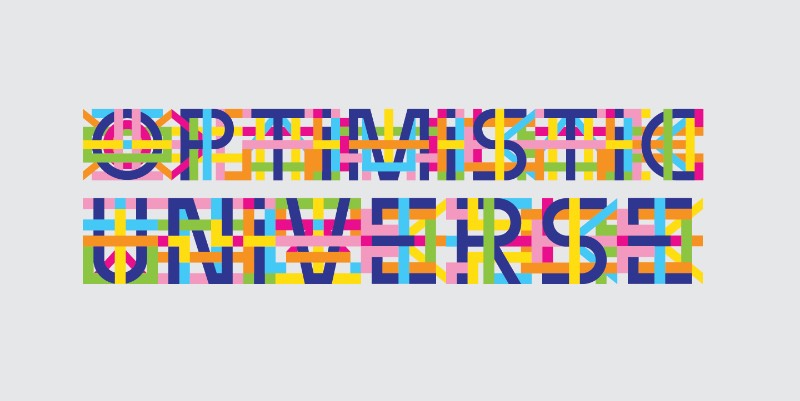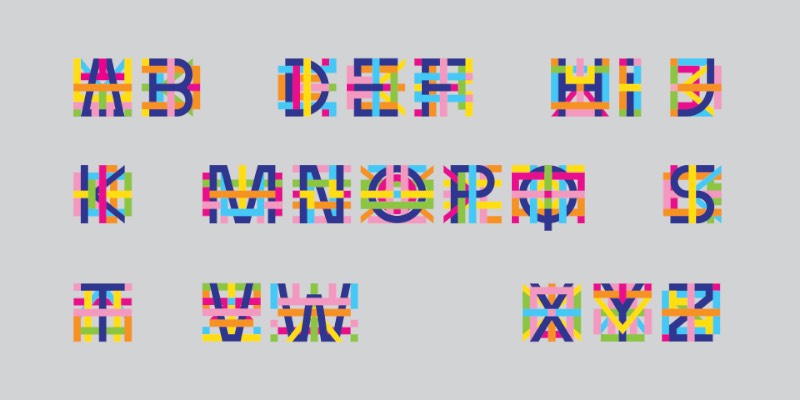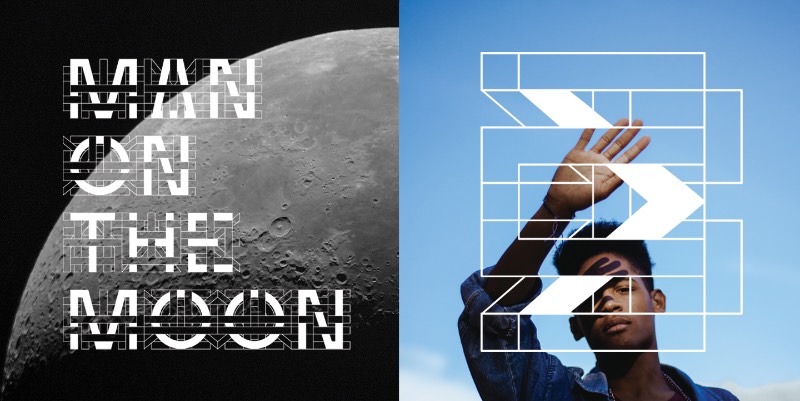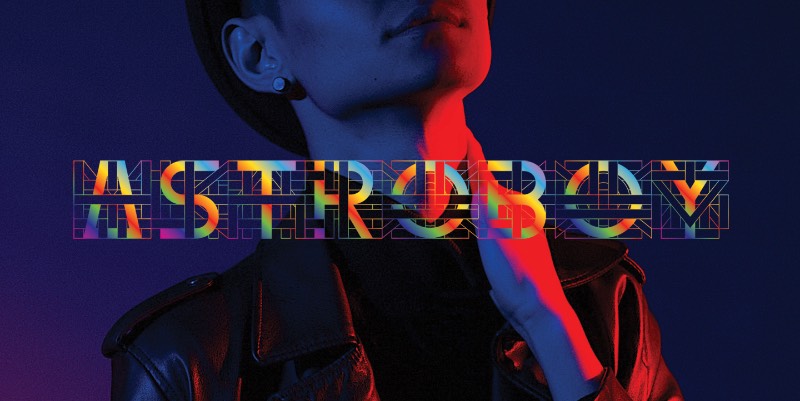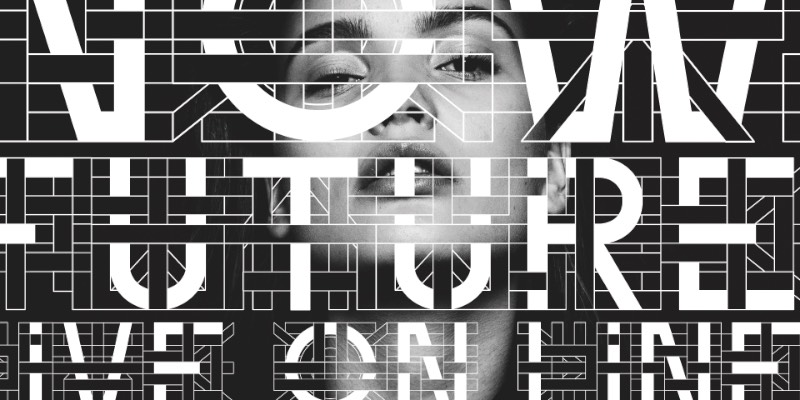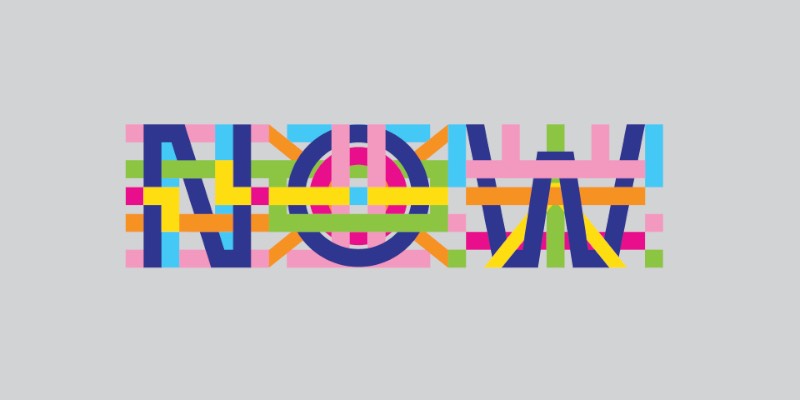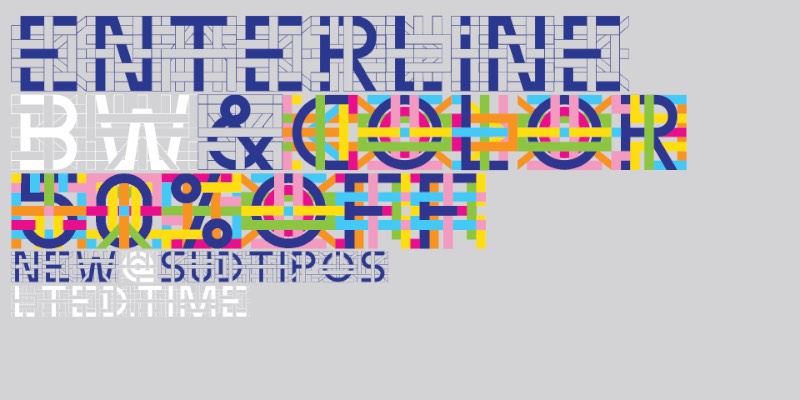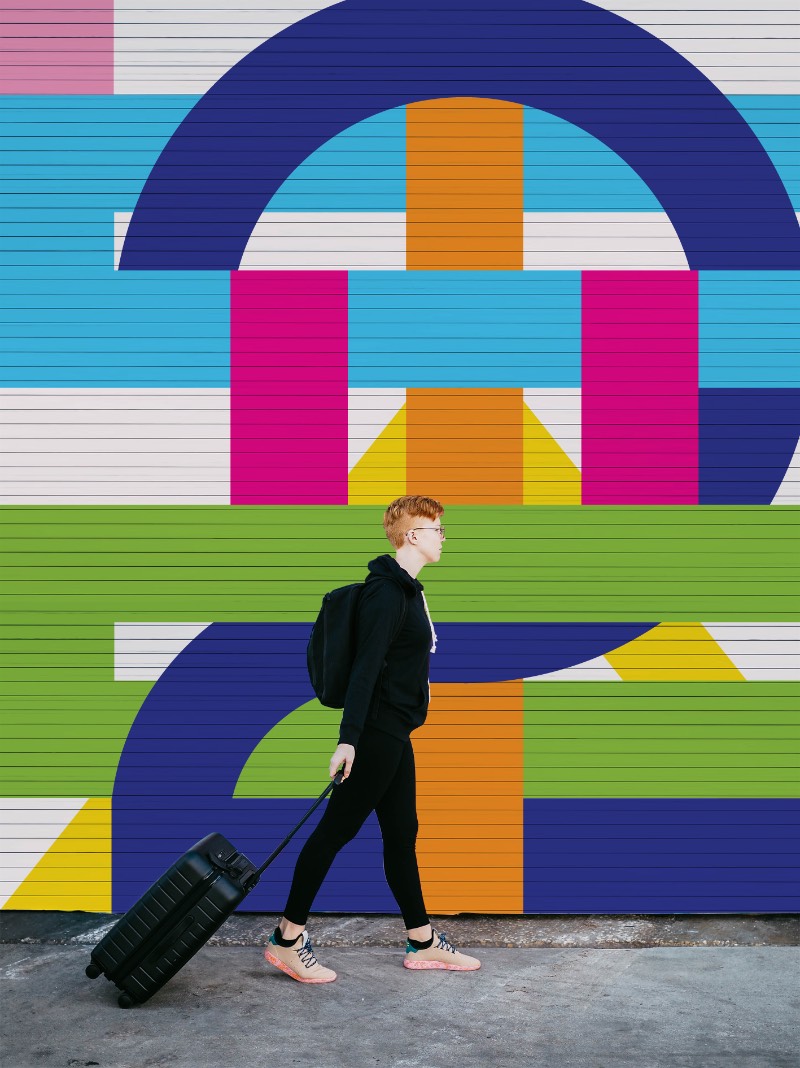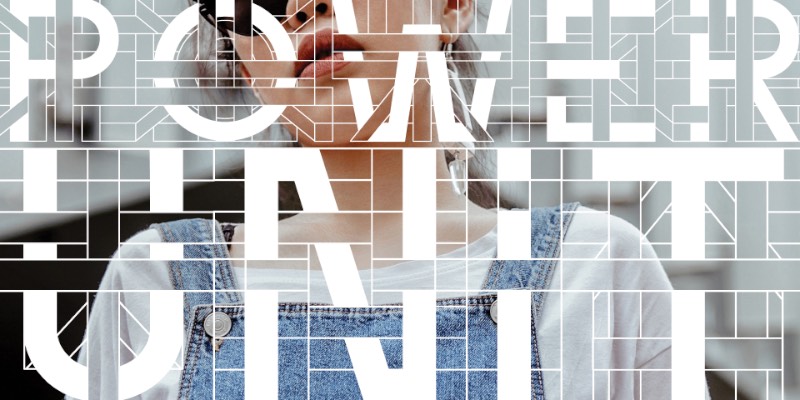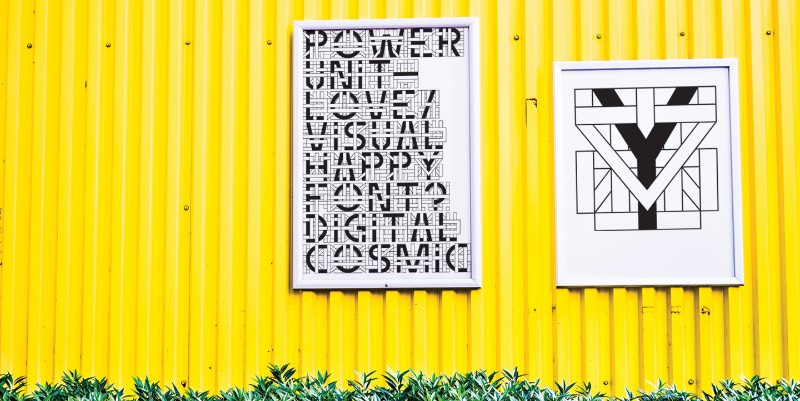
Enterline é uma colaboração tipográfica entre SAEL e Ale Paul para Sudtipos
Enterline é uma colaboração tipográfica entre SAEL e Ale Paul para Sudtipos como parte de um primeiro projeto que mistura ilustração com tipografia com a intenção de criar fontes cheias de cores. Se você gostar do que vai ver logo abaixo, saiba que essa fonte pode ser adquirida no link no final do artigo e ele vem em versões coloridas e uma versão em preto e branco que funcionam muito bem em qualquer aplicação.
Enterline assume com certa autoridade a expressão visual das fontes de cor. Quando explorada, a densidade de Enterline se torna líquida. Em sua narrativa, torna-se um padrão de infinitas variáveis e nuances. Em seu hibridismo, evolui como hiper-tipografia. Algo que eu nunca tinha visto antes nesse nível de complexidade visual.
Sael explora sua natureza gráfica repleta de diagonais, cores e formas padronizadas. Em cada letra de Enterline você pode ver como essa natureza gráfica obtém uma fonte de cores editável para ser utilizado em todos locais possíveis.
Uma estética futurista e robótica se mistura a um pulso que marca uma comunhão de códigos visuais, vetores e novas tecnologias. Dessa forma, foi criado um big bang mecânico otimista e multicolorido.